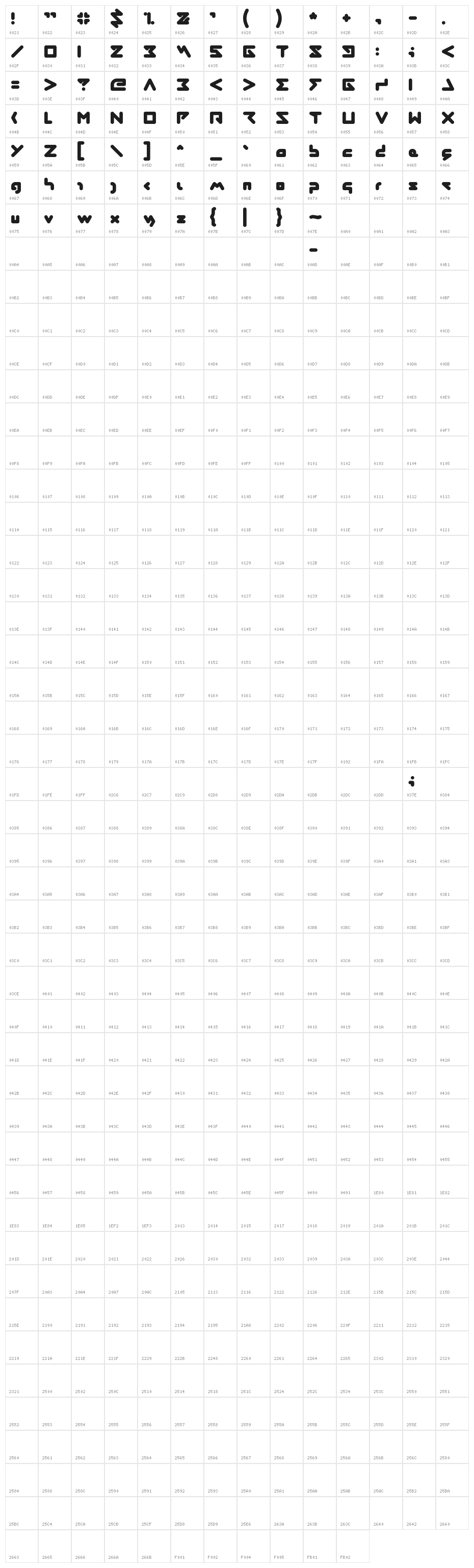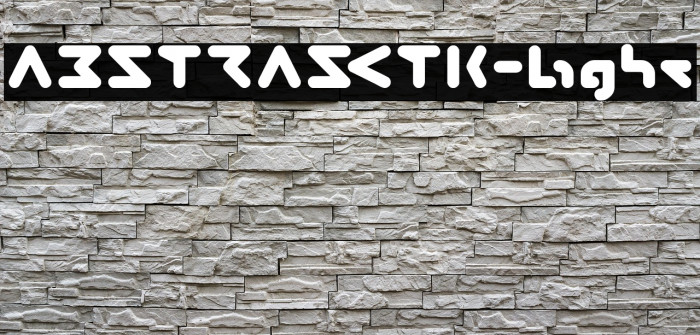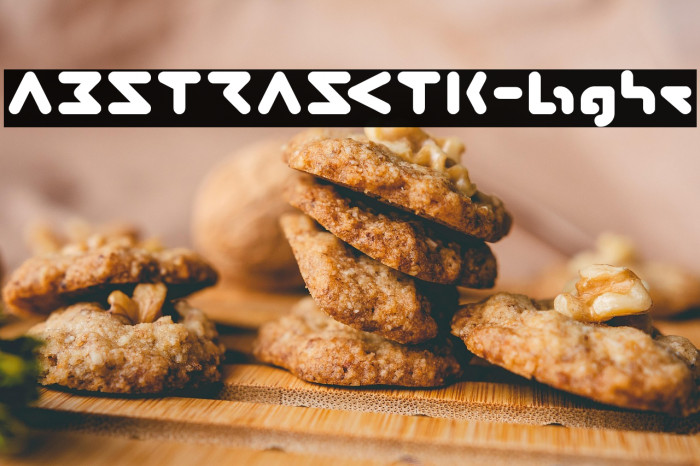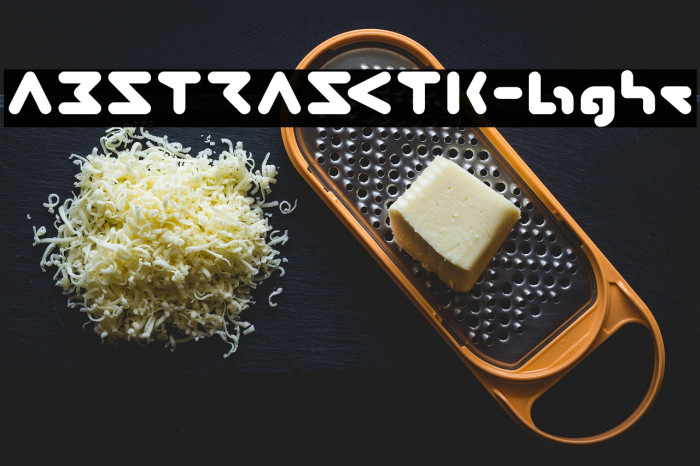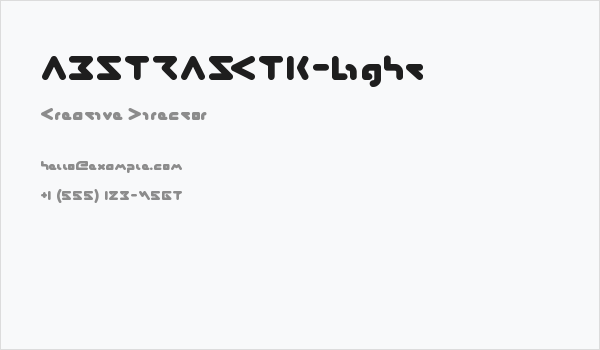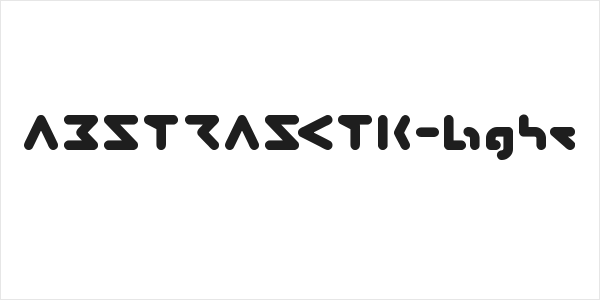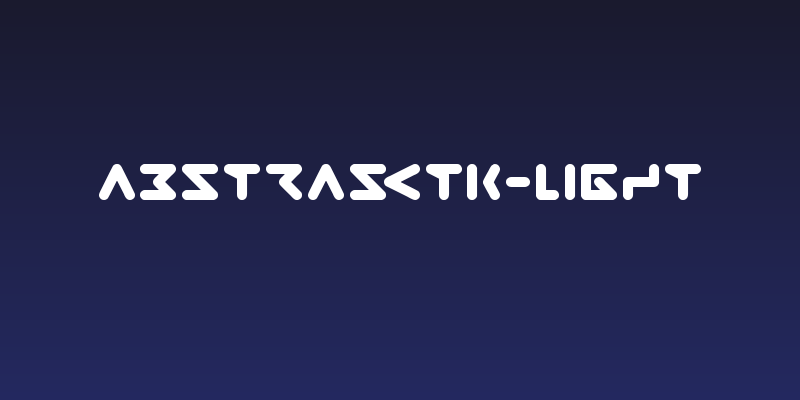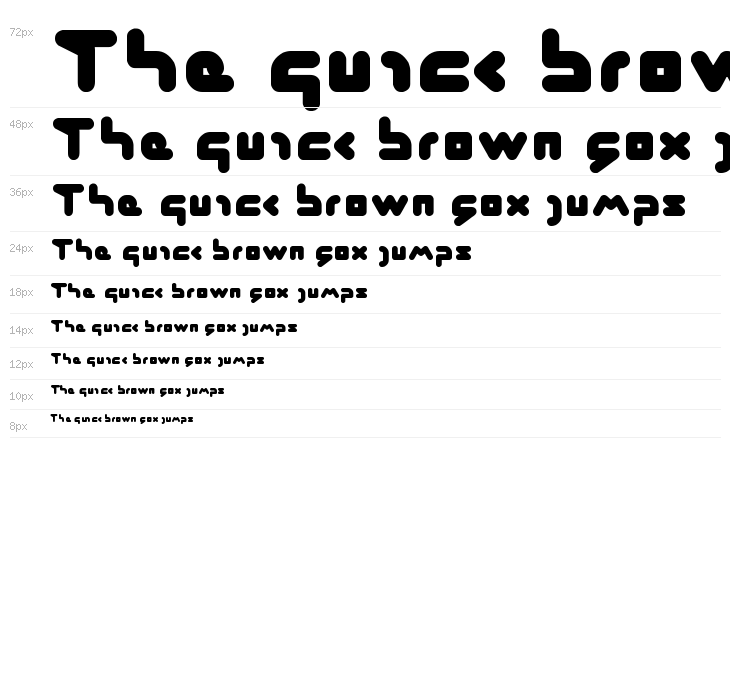
ABSTRASCTIK-Light Font
✎ Futuristic
| Категория | Futuristic |
| Рекомендуемые проекты | Ideal for sci-fi themed designs, video game titles, posters, and branding that requires a modern, edgy look. |